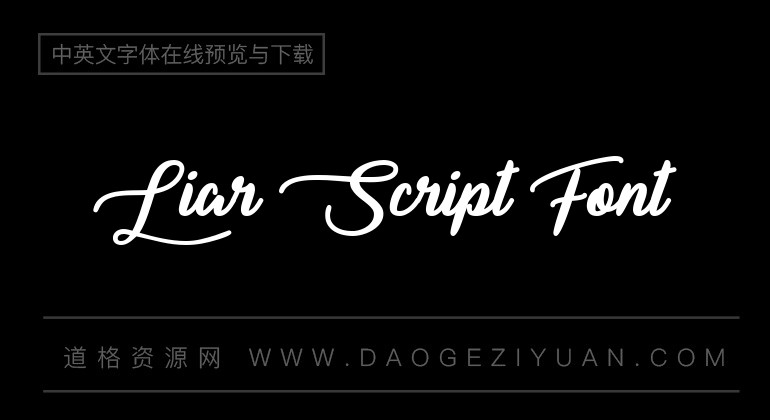
Liar Script Font
Liar Script字体是一种手写风格的字体,它具有艺术感和独特性,适合用于设计、标题、海报、广告和其他艺术项目中。该字体的笔画呈现出一种自然、流畅和有机的感觉,给文本带来了一种手写、自然和手工艺的感觉。Liar Script字体的字母和数字都有一些独特的特点,例如字母的上升和下降部分抽象和艺术性强,数字的笔画则表现出一些流畅和曲线美感。总的来说,Liar Script字体是一种独特、有机、艺术感强的字体,适合用于需要表现手工艺、艺术感和独特性的设计项目中。
Liar Script Font是一款非常不错的手写艺术字体,具有很好的视觉感,适合于文化类的宣传设计、商业类品牌的广告和产品包装设计以及个性化文字排版等较多场景。